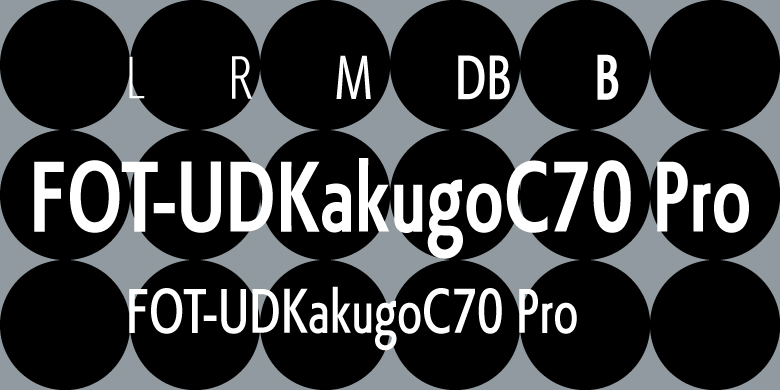
FOT-UDKakugoC70 Pro家族
字体品牌: Fontworks 设计师:Fontworks 字体分类:黑体 字体属性:外文 字符集:Unicode 发布时间: 2024
同样为了在有限的空间中美观且易于阅读地显示大量文字信息,"UD角ゴ_ラージ" 被设计成长体70%的字体,适用于小尺寸的各种详细显示。